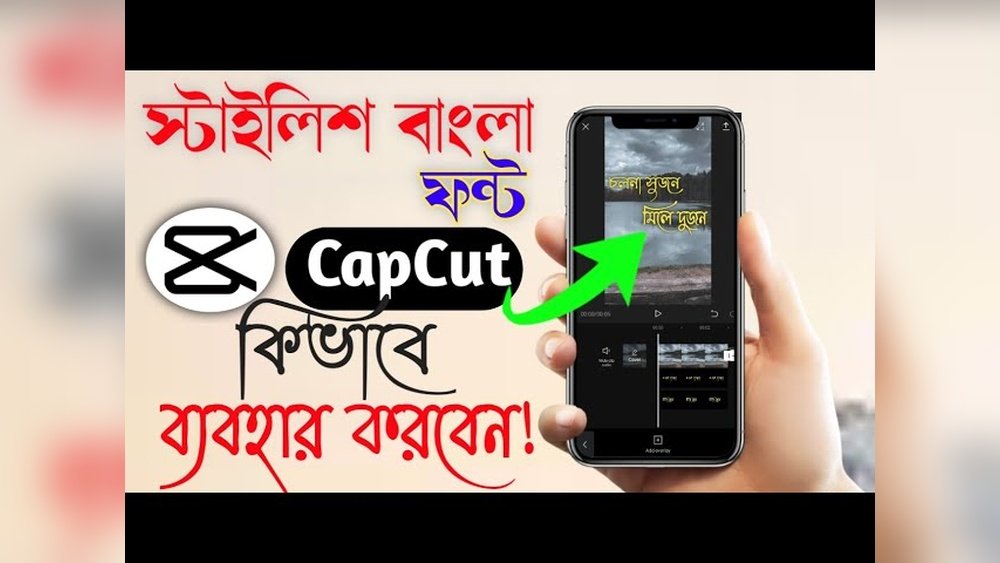
আপনি কি ক্যাপকাটে বাংলায় সুন্দর ও স্টাইলিশ ফন্ট ব্যবহার করতে চান? তাহলে আপনার জন্য রয়েছে একদম পারফেক্ট সমাধান—Bangla Font for Capcut। এই ফন্ট ব্যবহার করে আপনি আপনার ভিডিও এডিটিংকে এক নতুন মাত্রা দিতে পারবেন। আপনার ভিডিওর টেক্সট হবে আরও আকর্ষণীয়, পরিষ্কার এবং চোখে পড়ার মতো। আর সবচেয়ে ভালো কথা, এটি সহজেই ক্যাপকাটে যোগ করা যায়। আপনি যদি ভাবছেন কীভাবে ক্যাপকাটে বাংলা ফন্ট যোগ করবেন বা কোন ফন্টটি আপনার জন্য সেরা হবে, তাহলে এই আর্টিকেলটি পুরোটা পড়ে দেখুন। এখানে আমরা আপনাকে জানাবো Bangla Font for Capcut সম্পর্কে সব গুরুত্বপূর্ণ তথ্য এবং কীভাবে এটি ডাউনলোড ও ইনস্টল করবেন। এখনই আপনি Bangla Font for Capcut ডাউনলোড করুন এবং আপনার ভিডিওগুলোকে আরও প্রফেশনাল লুক দিন। আপনার ভিডিও এডিটিং যাত্রাকে আরও সহজ ও মজাদার করতে Bangla Font for Capcut একটি অপরিহার্য টুল। আপনার স্বপ্নের মতো ভিডিও তৈরি করার জন্য আজই এটি ব্যবহার শুরু করুন!
Bangla Font For Capcut: পরিচিতি ও প্রয়োজনীয়তা
Bangla Font for Capcut হলো একটি বিশেষ ফন্ট প্যাক যা ক্যাপকাট ভিডিও এডিটিং অ্যাপে বাংলা ভাষায় সুন্দর ও স্পষ্ট লেখা তৈরিতে সাহায্য করে। বাংলা ফন্টের মাধ্যমে ভিডিওর মেসেজ আরও ভালোভাবে বোঝানো যায়। বাংলা ভাষাভাষী ব্যবহারকারীদের জন্য এটা খুবই প্রয়োজনীয়।
বাংলা ফন্টের ব্যবহার ভিডিওর মান বৃদ্ধি করে। সহজে বাংলা শব্দের সঠিক প্রকাশ ঘটে। তাই ক্যাপকাট ব্যবহারকারীদের জন্য বাংলা ফন্টের গুরুত্ব অপরিসীম।
বাংলা ফন্ট ব্যবহারের সুবিধা ও প্রয়োজন
বাংলা ফন্ট ব্যবহার করলে ভাষার স্বতন্ত্রতা বজায় থাকে। বাংলা ভাষায় ভিডিও তৈরি করলে দর্শকের সাথে সংযোগ বাড়ে।
- বাংলা ভাষার সঠিক প্রকাশ
- দর্শকের কাছে সহজবোধ্যতা
- ভিডিওর প্রফেশনাল লুক
- সাংস্কৃতিক পরিচয় রক্ষা
বাংলা ফন্ট ছাড়া ভিডিওতে বাংলা লেখা সঠিকভাবে দেখা যায় না। অনেক সময় গড়মিল হয়। তাই ফন্ট ব্যবহারের প্রয়োজন খুবই জরুরি।
ভিডিও সাজানোর ক্ষেত্রে বাংলা ফন্টের ভূমিকা
ভিডিওর টেক্সট হলো গুরুত্বপূর্ণ অংশ। বাংলা ফন্ট থাকলে ভিডিওর মেসেজ স্পষ্ট হয়। দর্শক সহজে বুঝতে পারে।
ফন্টের মাধ্যমে ভিডিওর সৌন্দর্য বৃদ্ধি পায়। ভালো ফন্ট ব্যবহার করলে ভিডিওর পেশাদারিত্ব বেড়ে যায়।
| বাংলা ফন্টের সুবিধা | ভিডিও এডিটিংয়ে প্রভাব |
|---|---|
| সঠিক বাংলা অক্ষর প্রদর্শন | দর্শকের কাছে পরিষ্কার মেসেজ পৌঁছায় |
| স্টাইলিশ ও আকর্ষণীয় লেখা | ভিডিওর দৃষ্টিনন্দনতা বৃদ্ধি পায় |
| ভাষাগত ঐতিহ্য রক্ষা | বাংলা ভাষার মর্যাদা বৃদ্ধি পায় |
| সহজ পাঠযোগ্যতা | দর্শক দীর্ঘসময় ভিডিও দেখে |
Bangla Font for Capcut ভিডিও এডিটিংয়ে অপরিহার্য। এটি ভিডিওর মান ও প্রভাব বাড়ায়।
Capcut-এর জন্য সেরা বাংলা ফন্টের বৈশিষ্ট্য
Bangla Font for Capcut ভিডিও এডিটিংয়ে বাংলা ভাষার স্বতন্ত্রতা ও শৈলী এনে দেয়। সেরা বাংলা ফন্টের সাহায্যে ভিডিওর পাঠযোগ্যতা, আর্কষণ ও ব্যবহারকারীর অভিজ্ঞতা উন্নত হয়। সঠিক ফন্ট নির্বাচন ভিডিওর প্রভাব বাড়ায় এবং দর্শকের সাথে সহজেই সংযোগ স্থাপন করে।
ফন্টের পাঠযোগ্যতা ও স্পষ্টতা: ব্যবহারকারীর সুবিধা
বাংলা ফন্টের প্রধান লক্ষ্য হল পাঠযোগ্যতা ও স্পষ্টতা বজায় রাখা।
- ছোট পর্দায়ও ফন্ট যেন পরিষ্কার দেখা যায়।
- প্রতিটি অক্ষর সহজে চিনতে পারা যায়।
- দীর্ঘ সময় পড়ার পরও চোখে চাপ পড়ে না।
- ভিডিওর কন্টেন্ট দ্রুত বোঝা যায়।
স্টাইলিশ ও আধুনিক ডিজাইন: ভিডিওর আকর্ষণ বৃদ্ধি
স্টাইলিশ বাংলা ফন্ট ভিডিওর শৈলীকে আধুনিক করে তোলে।
- নান্দনিক ও কালচারাল স্পর্শে ভরপুর।
- ভিডিওর মূল ভাব প্রকাশে সহায়ক।
- বিভিন্ন ডিজাইন থিমের সাথে মানানসই।
- দর্শকের নজর আকর্ষণ করে।
Unicode সাপোর্ট: সব ডিভাইসে সহজে প্রদর্শন
Unicode সমর্থিত বাংলা ফন্ট সব ডিভাইসে সঠিকভাবে প্রদর্শিত হয়।
- মোবাইল, ট্যাবলেট ও কম্পিউটারে সমানভাবে কাজ করে।
- অপেরেটিং সিস্টেমের সীমাবদ্ধতা নেই।
- বাংলা অক্ষর ও চিহ্ন সঠিকভাবে দেখা যায়।
- ভিন্ন প্ল্যাটফর্মে ফন্ট বিকৃত হয় না।
Capcut-এ Unicode সাপোর্ট ভিডিও সম্পাদনায় সমস্যা দূর করে।
বিভিন্ন থিম ও মুডের জন্য ফন্টের বৈচিত্র্য
বাংলা ফন্টের বৈচিত্র্য ভিডিওর মুড অনুযায়ী পরিবর্তনের সুযোগ দেয়।
| থিম/মুড | ফন্ট বৈশিষ্ট্য | ব্যবহার |
|---|---|---|
| আনন্দময় | উজ্জ্বল, হাসিখুশি স্টাইল | বাচ্চাদের ভিডিও, উৎসবের ভিডিও |
| গম্ভীর | দৃঢ় ও পরিষ্কার লাইন | শিক্ষামূলক, তথ্যবহুল ভিডিও |
| রোমান্টিক | নরম ও কারুকার্যপূর্ণ ফন্ট | প্রেমের গল্প, নাটক |
| আধুনিক | সিম্পল ও ক্লিন ডিজাইন | টেকনোলজি, কর্পোরেট ভিডিও |
এভাবেই ফন্টের বৈচিত্র্য ভিডিওর আবেগ ও উদ্দেশ্য সম্পূর্ণ করে।